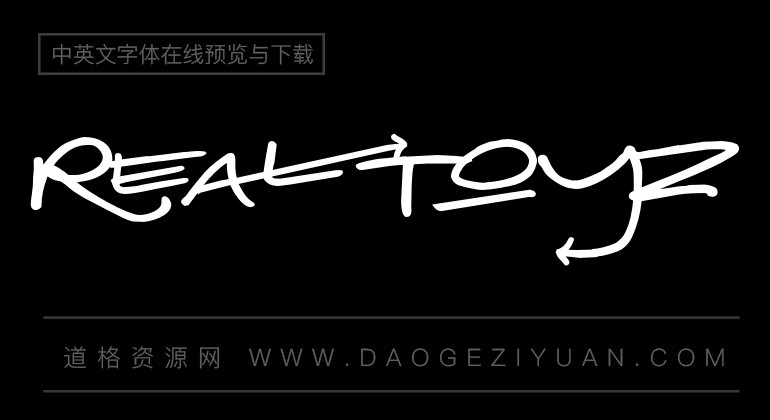
Real Toyz
Real Toyz 是一种漫画和卡通风格的字体,它具有轻松、有趣和幽默的特点。它的字形清晰明朗,有时会带有一些圆润的角度和弧度,常常用于漫画、动画、游戏和其他儿童相关的设计中。 Real Toyz 字体家族包括 Regular、Bold 和 Italic 三种样式,每种样式都具有不同的粗细和风格。它适用于大多数设计软件,并且可以在 Windows、Mac OS 和 Linux 等操作系统上使用。 Real Toyz 字体通常被用于儿童书籍、海报、广告、玩具包装、动画游戏和其他儿童相关的设计中,因为它能够很好地传达童趣和幽默感,让人们感到快乐和轻松。
Real Toyz是一款非常不错的手写艺术字体,具有很好的视觉感,适合于文化类的宣传设计、商业类品牌的广告和产品包装设计以及个性化文字排版等较多场景。